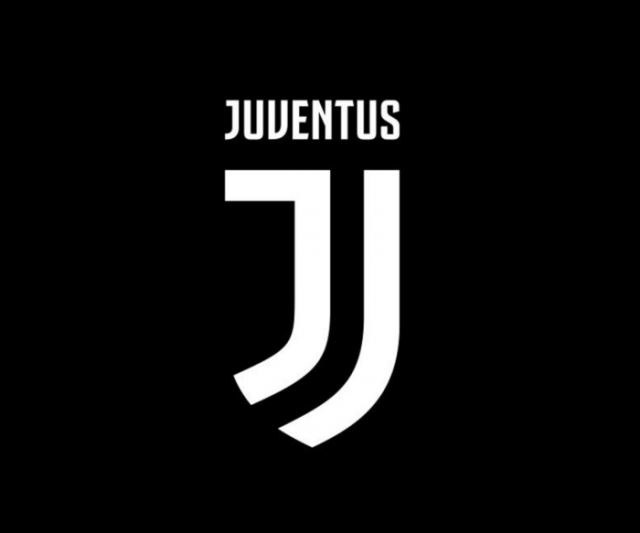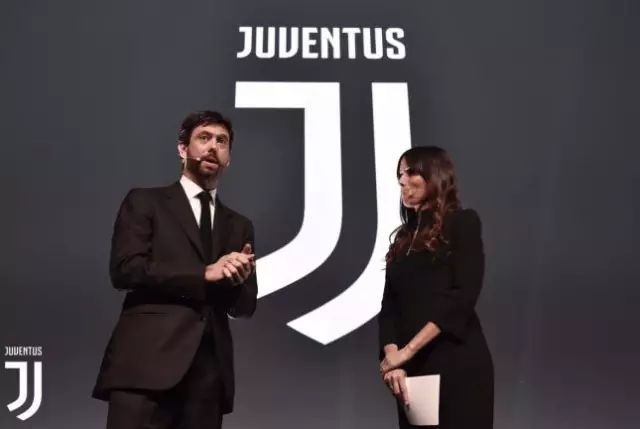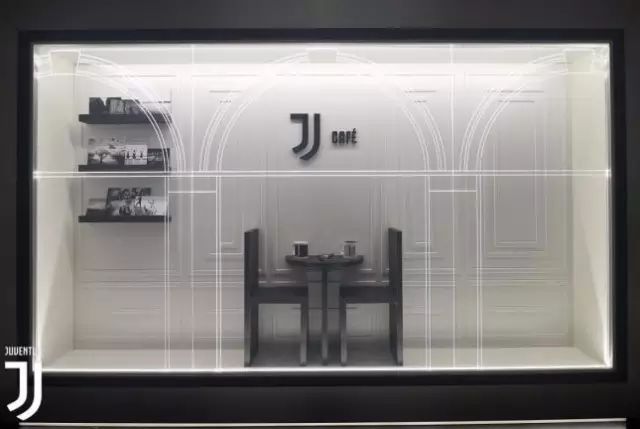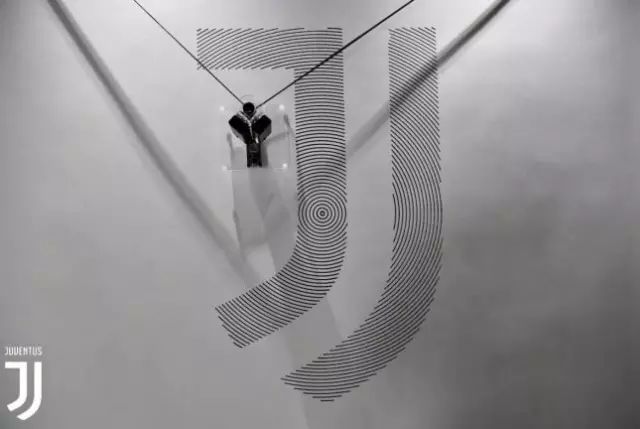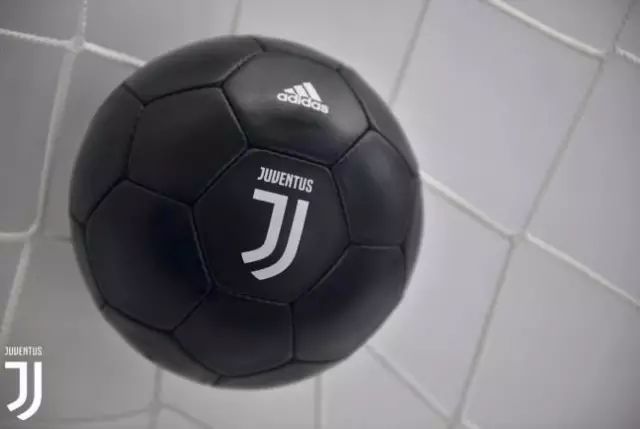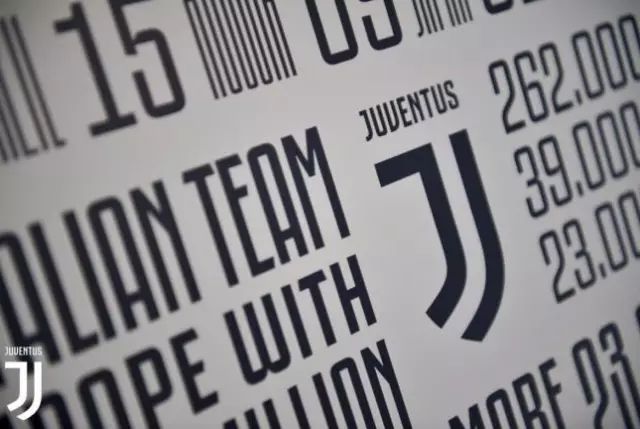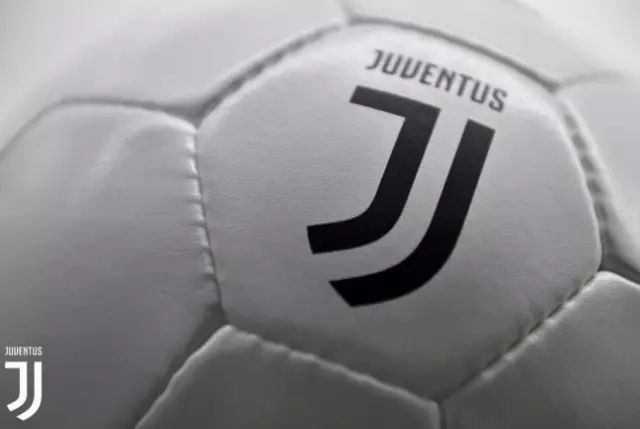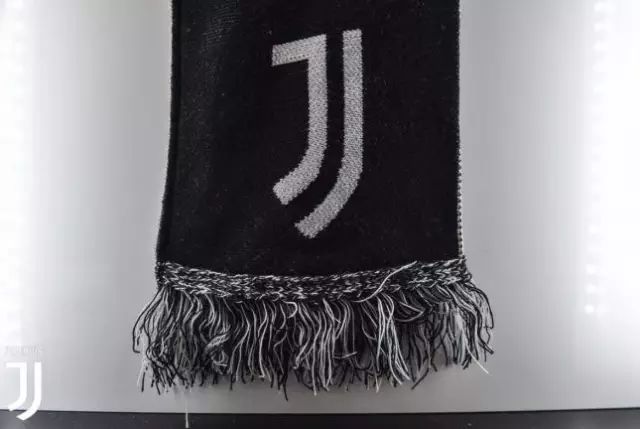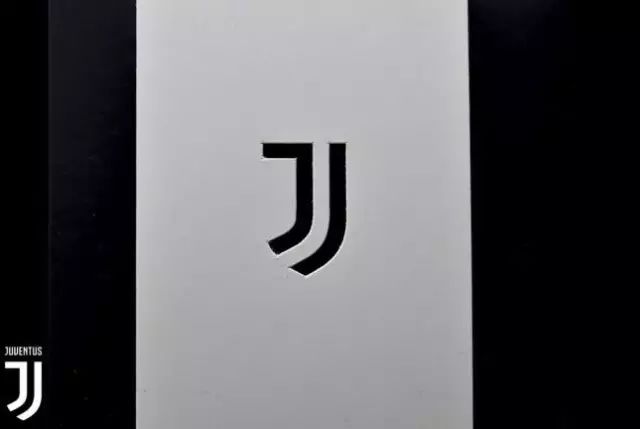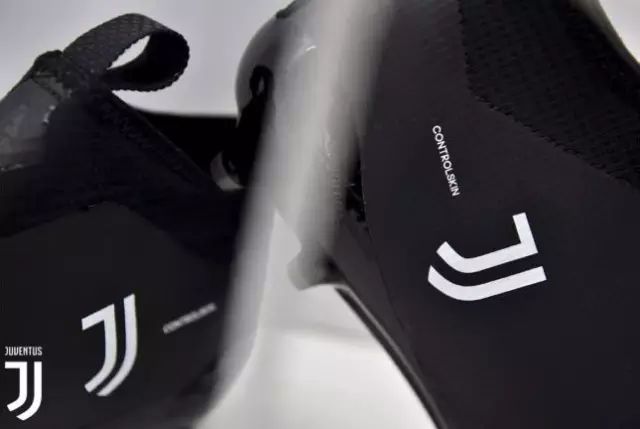
尤文图斯足球俱乐部品牌形象
意甲豪门尤文图斯足球俱乐部,其标志性的黑白相间的球衣,我们是非常熟悉的了。现在,尤文图斯将黑白转换为更加纯粹的“J”,不能不说是一个绝妙的创意。
2017年1月16日晚,尤文图斯举行了一场主题为“Black and White and More”的活动。在这次盛大的活动中,尤文图斯宣布揭晓全新俱乐部队徽。
新队徽的变化是具有历史意义,组成要素正是Juventus的“J”,这个“J”除了代表Juventus,意甲联赛冠军盾牌与经典的斑马条纹。新的形象由 Interbrand 公司打造。
尤文图斯足球俱乐部(Juventus Football Club S.P.A)是一家位于意大利皮埃蒙特大区都灵市的足球俱乐部,成立于1897年11月1日,是意大利国内历史最为悠久的俱乐部之一,也是夺得意大利足球甲级联赛冠军最多的球队。
尤文图斯俱乐部的标志历史: